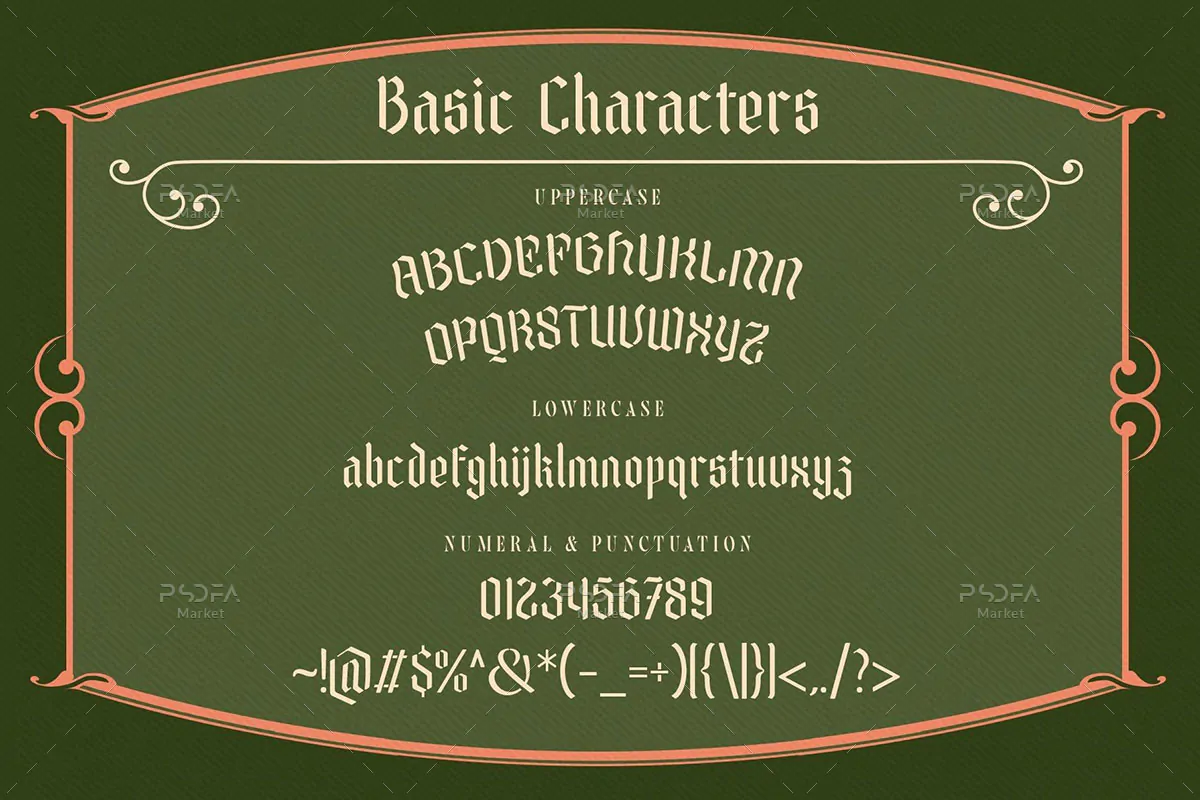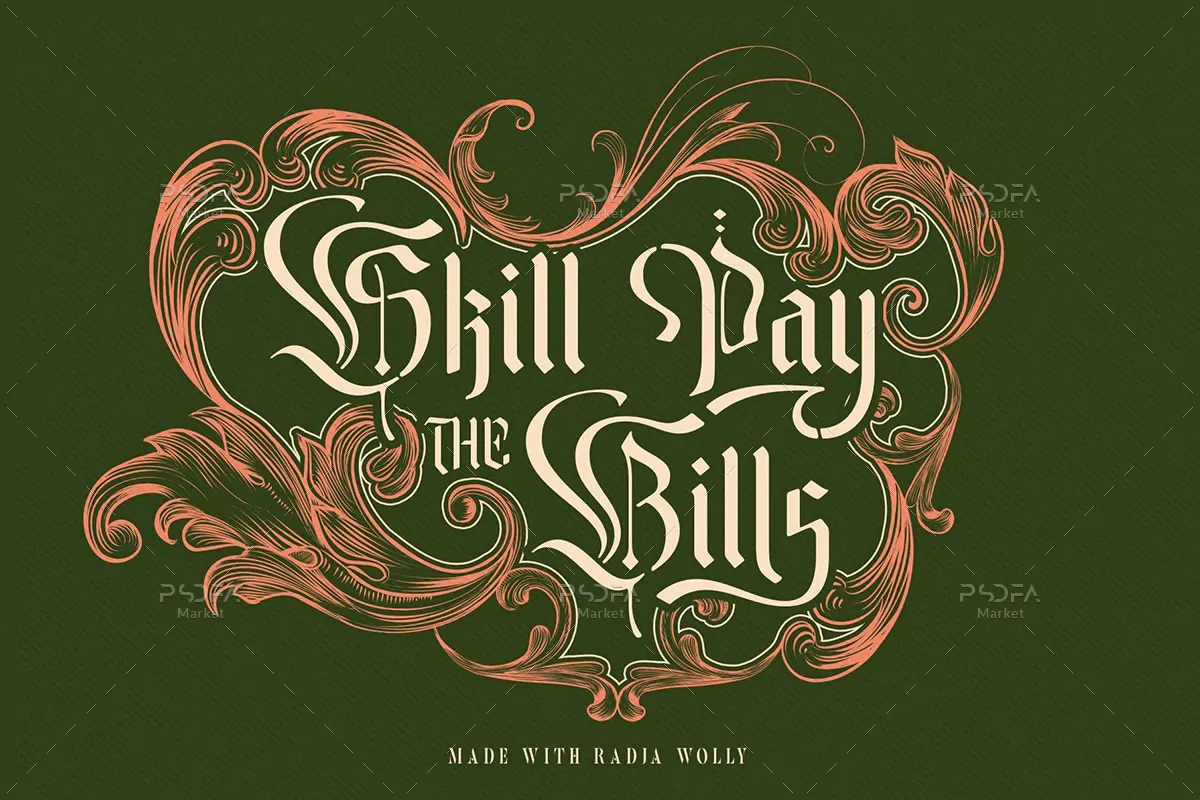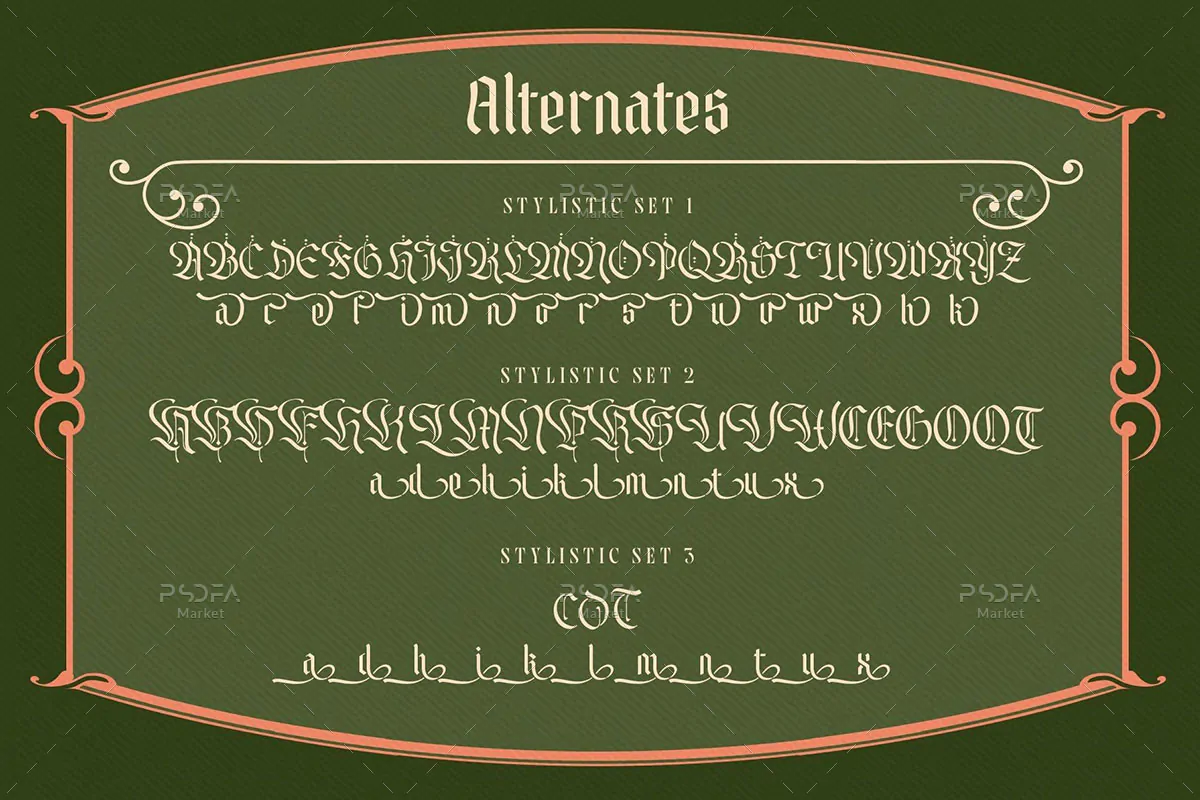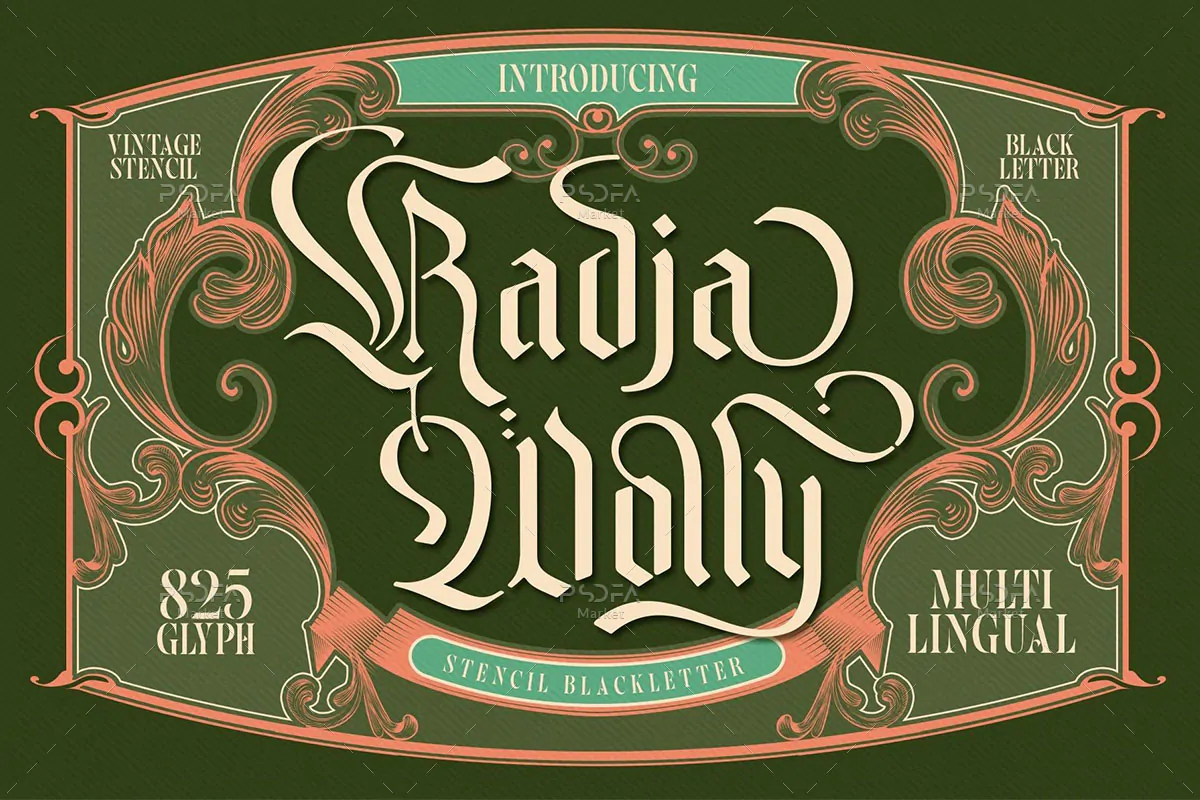
فونت کلاسیک انگلیسی Radja Wolly
فونت کلاسیک انگلیسی
فونت کلاسیک انگلیسی Radja Wolly یک قلم بلک لتر فوق العاده زیبا به سبک فونتهای قدیمی است که مناسب جهت استفاده در طرح و پروژههای مختلف به خصوص طراحی انواع پوستر میباشد. فونت Radja Wolly با وزن معمولی طراحی شده است که میتوانید از آن در طراحی پوستر، کارت ویزیت، بسته بندی محصولات، ظروف یکبار مصرف، بطریهای نوشیدنی و … استفاده کنید. نسخه وب این قلم زیبا نیز در فایل محصول قرار دارد که میتوانید در طراحی صفحات وب از آن استفاده کنید.